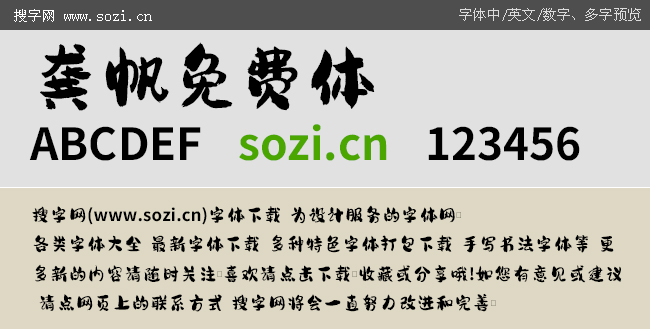
龔帆免費(fèi)體
搜字網(wǎng)給大家提供一款龔帆免費(fèi)體中文字體下載,該字體是一款免費(fèi)商用手寫書法字體,該字體將傳統(tǒng)與現(xiàn)代的手寫結(jié)合,字跡飛揚(yáng),筆斷意連,適用于平面宣傳設(shè)計(jì)、網(wǎng)頁(yè)設(shè)計(jì)、海報(bào)設(shè)計(jì)等應(yīng)用(淘寶搜龔帆字庫(kù)可買單字授權(quán))。